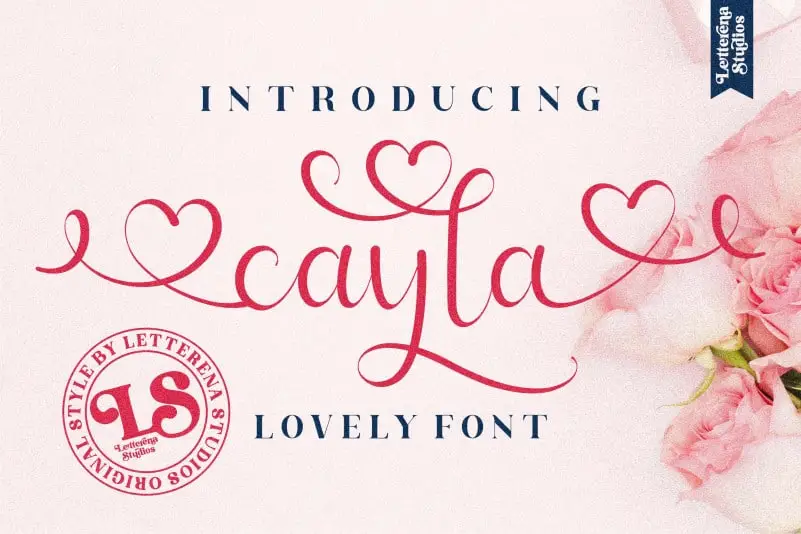
Cayla Calligraphy Font – Download Grátis
A fonte ‘Cayla Calligraphy Font’ é uma elegante fonte feita à mão com traços finos e delicados, perfeita tanto para criações online quanto para projetos DIY de calligrafia. Se você está procurando por opções criativas para Instagram posts ou quaisquer trabalhos de decorativa hand-lettering, esta font fará que qualquer ideia original se torne uma obra de arte realmente única! Uma característica interessante é o fato de ser PUA encoded, o que significa que pode acessar facilmente todos os caracteres e traços finos desta fonte. Estamos ansiosos para compartilhar este artesanal toque no seu design.